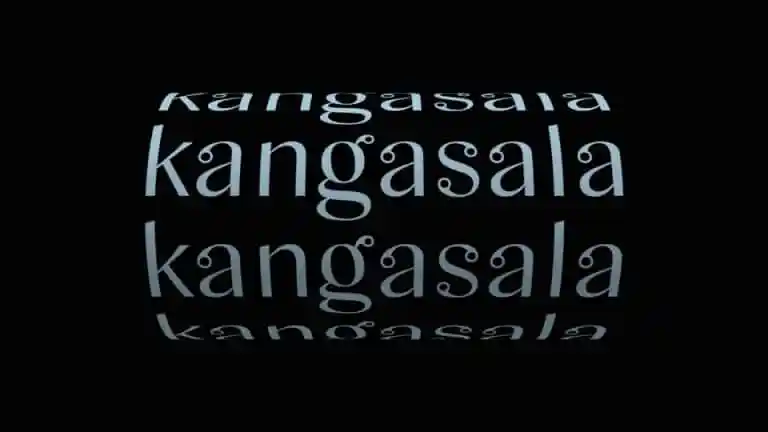
A Kangasala Sans Serif Font é uma escolha perfeita para aqueles que buscam uma mistura poética entre uma fonte séria e uma fonte sem serif. Esta elegante fonte sans serif é ideal para criar logos memoráveis e títulos memoráveis, oferecendo inúmeras possibilidades de aplicação em projetos gráficos ou editoriais. Com sua rica personalidade, a Kangasala oferece uma harmonia única que se combina perfeitamente com vários tipos de fontes existentes. Suas linhas finas e suaves proporcionam um contraste interessante, dando ao seu design o toque de sofisticação desejado. Este tipo de fonte é especialmente útil para projetos visuais que buscam uma transição delicada entre a simplicidade da serif e a modernidade da sans-serif. A Kangasala Sans Serif é um recurso valioso para designers, oferecendo flexibilidade e estética em qualquer projeto gráfico ou editorial. É perfeitamente adaptável a uma variedade de aplicações e pode ser combinada com outras fontes sem serif para criar design visual moderno e único. Como designer ou apaixonado por design, o Kangasala é um companheiro ideal para suas próximas criações visuais.